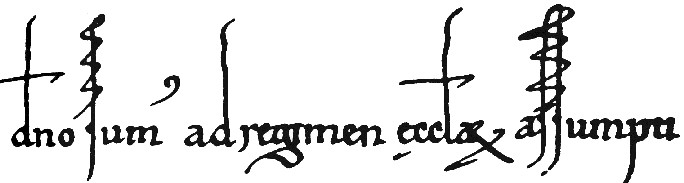
![]() etwa 2. Jahrhundert v. Chr. - 2. Jahrhundert n. Chr. | ||
| für Bücher | für Dokumente | für Briefe und Notizen |
![]() Quadrata etwa 3. - 4. Jahrhundert |
![]() Rustica etwa 2.- 6. Jahrhundert |
![]() die currente Form der Kapitale etwa ab 2. Jahrhundert |
![]() Unciale 3. - 6. Jahrhundert |
![]() halbunciale etwa 5.- 7. Jahrhundert |
![]() iuengere roem. cursiue = jüngere römische Cursive 4. - 9. Jahrhundert |
![]() karolingische Minuskel etwa ab 9. Jahrhundert | ||
![]() gotische Minuskel etwa ab 12. Jahrhundert |
![]() diplomatische Minuskel 11.- 13. Jahrhundert |
![]() Textura 14. - 16. Jahrhundert | ![]() Cursive etwa ab 13. Jahrhundert Im 15. Jhdt. waren vier verschiedene Versionen im Gebrauch |
![]() Rotunda etwa ab 14. Jahrhundert |
![]() Notula etwa ab 15. Jahrhundert |
![]() Cancellaresca etwa ab 16. Jahrhundert |
![]() Schwabacher etwa ab 15. Jahrhundert |
![]() Cantzley etwa ab 16. Jahrhundert | |
| für Bücher | für Dokumente | für Briefe und Notizen |
![]() Fraktur etwa ab 16. Jahrhundert |
![]() Kanzleischrift etwa ab 17. Jahrhundert |
![]() Kurrente etwa ab 16. Jahrhundert |
Humanistische Buchschrift etwa ab 15. Jahrhundert |
![]() Humanistische Canzleischrift etwa ab 16. Jahrhundert |
![]() Humanistische Cursive etwa ab 16. Jahrhundert |
![]() Antiqua ab Ende des 15. Jahrhunderts |
![]() Rundschrift etwa um 1875 |
![]() deutsche Schreibschrift etwa ab 18. Jahrhundert |
| für Bücher | für Dokumente | für Briefe und Notizen |
![]() Grotesk und ![]() Egyptienne etwa ab 19. Jahrhundert |
![]() Jugendstil und ![]() Tannenberg um 1915 / um 1930 |
![]() Lateinische Schreibschrift etwa ab 18. Jahrhundert |
![]() Helvetica etwa ab 1960 |
![]() "Data" für Schecks, ab 1965 |
![]() Schreibmaschine-Antiqua ab 20. Jahrhundert |
Anmerkung : das Aussehen der Schrift steht auch in Zusammenhang mit dem Schreibmaterial. Es macht durchaus einen Unterschied, ob die Schrift in Stein gehauen, als Notizen auf Wachstafeln gekritzelt oder als Dokument auf Pergament geschrieben wird. Die Erfindung bzw. der vermehrte Einsatz von Papier etwa ab dem 11. Jahrhundert ergab ganz neue Möglichkeiten der Federführung.
Seit der Erfindung der beweglichen Lettern müssen nicht mehr alle Veröffentlichungen mühsam mit der Hand kopiert werden, der Druck von Büchern und Zeitschriften macht das unnötig.
Vor 100 Jahren war es sehr beliebt, mit möglichst vielen Schnörkeln zu schreiben. Heute können das nur wenige, aber solche Schönschriften sind immer noch beliebt. Man findet solche Schriten z.B. auf einer Karte eines Geschenkabo oder als Gedicht in einem Buch.
Wurde früher noch viel mit der Hand geschrieben, ist es heute eher der Computer, der uns diese Arbeit abnimmt. Die Entwicklung der Schrift hat sich vom Stein zum elektronischen Dokument vollzogen. Aber auf verzierte Schriften braucht niemand zu verzichten. Für besondere Anlässe gibt es entsprechende Fonts in jedem Textverarbeitungsprogramm. Dieser Wandel hat dazu geführt, daß manche mit der Hand nur noch in Blockschrift schreiben können.